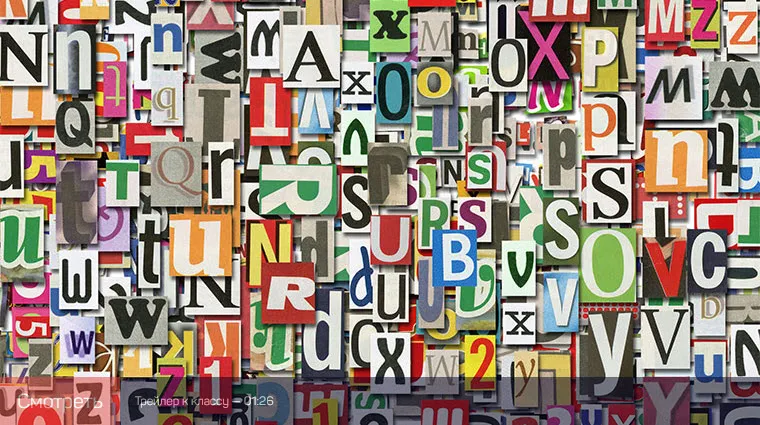
Выразительные средства: Шрифт
Шрифтовые композиции — это вершина графического дизайна, требующая понимания исторического контекста и правил построения знаков. Здесь разбирается, почему кириллица требует иного подхода, чем латиница, и как перестать следовать устаревшим мифам, например, запрету на использование более двух шрифтов в макете.
В материале детально рассматриваются классификации шрифтов — от антиквы и гротесков до брусковых и декоративных начертаний. Вы узнаете, как подбирать гармоничные сочетания шрифтов, корректировать межбуквенные расстояния и адаптировать типографику под конкретное визуальное сообщение. Курс будет полезен дизайнерам, желающим перейти от интуитивного подбора шрифтов к осознанному проектированию визуальных коммуникаций.
- Краткая история письменности
- Serif - Антиква
- Sans Serif - Гротеск
- Slab - Брусковый
- Декоративные шрифты
- Рукописные шрифты
- Русский & Nerusskiy
- Расстояния между знаками
- Нарушая правила